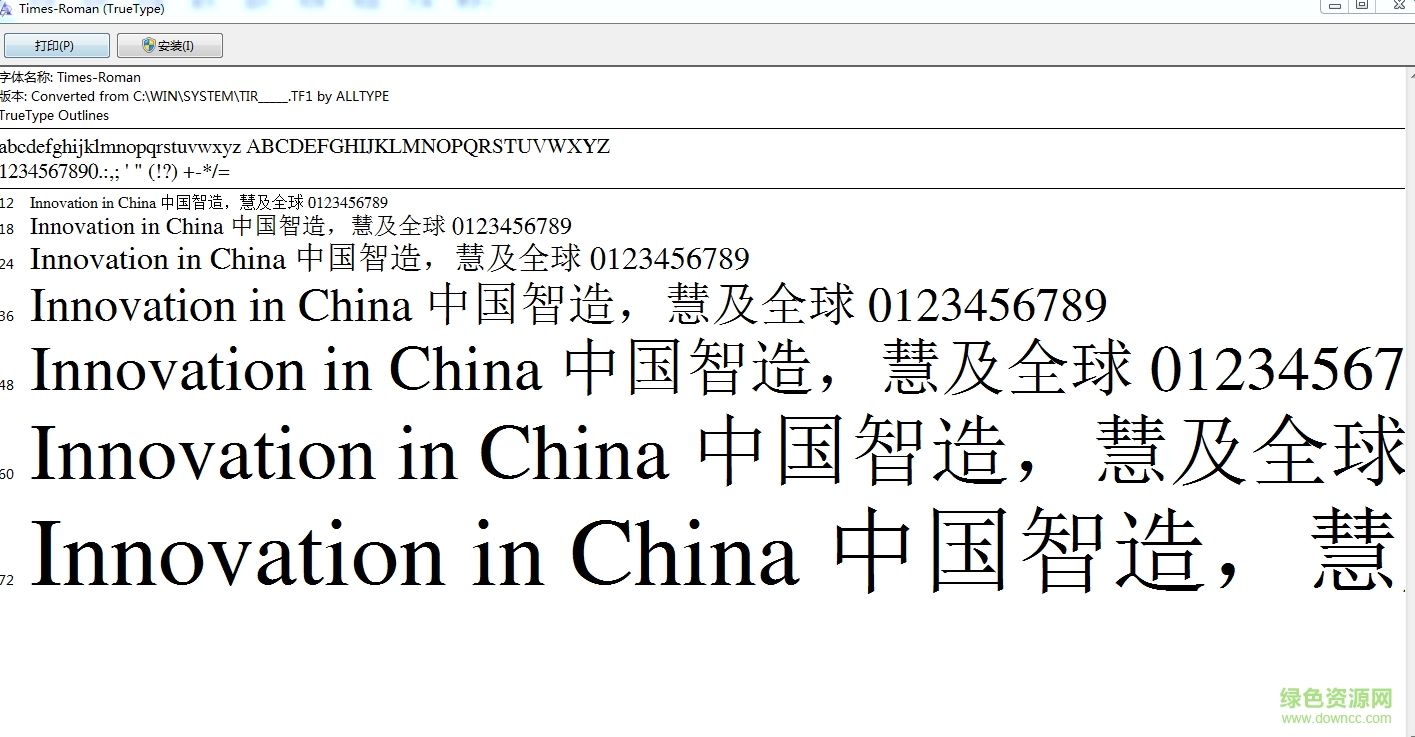
times-roman 是什么字體?times-roman-常規(guī)字體是一款過(guò)渡襯線字體,該類字體又稱巴洛克體,times-roman gb2312字體非常經(jīng)典,字形優(yōu)美柔軟,應(yīng)用范圍廣泛,有需要者歡迎在綠色資源網(wǎng)下載!
羅馬字體或襯線體(roman,serif);無(wú)襯線體(sanserif);手寫體(script);雕刻字系(glayphic);典籍體字系(Classical);裝飾體字系(decorative); 展示體字系(Display);當(dāng)代字體字系(Contemporary);符號(hào)字系(Symbol)…